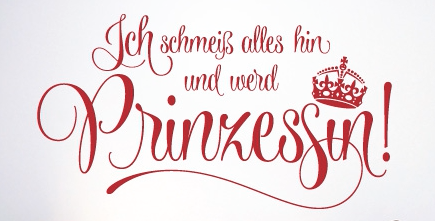
Welche Schriftart ist das?
ich bin auf der suche nach dieser schriftart!
mir gefällt diese schriftart vom wandtattoo und möchte sie gerne in meiner schriftensammlung speichern.
leider hab ich bis jetzt nicht raus gefunden wie sie heisst.
Und dann die OpenType-Feature anwenden, damit die Schwünge und Buchstabenunterschiede (siehe das Doppel-s oben) entstehen.
Hier ein paar Vertreter dieses Stiles: